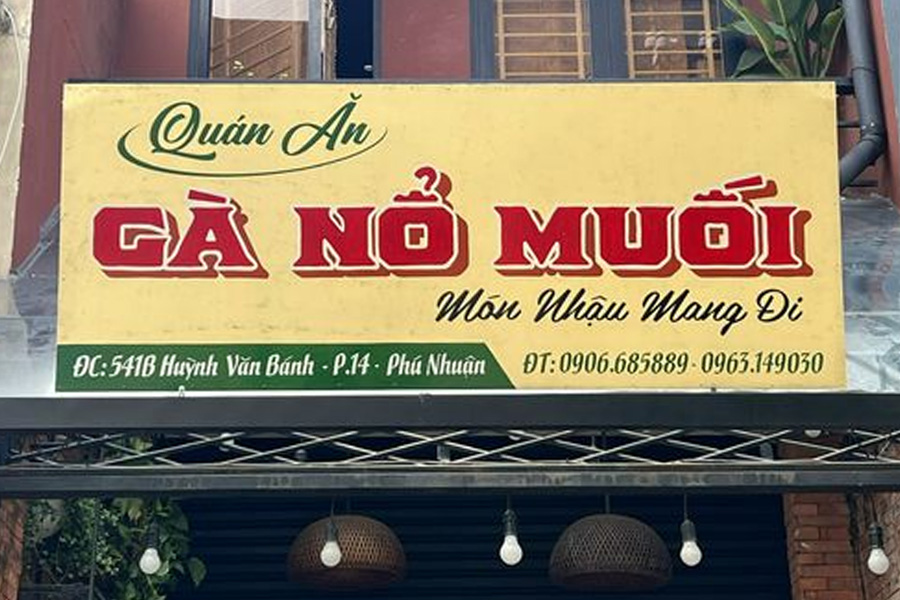
Là một người thiết kế và việt hóa font chữ, mình có một ấn tượng đặc biệt tới các font chữ bảng hiệu xưa của Việt Nam ta trong thời kỳ bao cấp. Thời kỳ này đã để lại dấu ấn rõ rệt trong các bảng hiệu của những cửa hàng tạp hóa, tiệm cắt tóc hay quán cafe…. Font chữ thời bao cấp Việt Nam không chỉ mang đến một nét mộc mạc, giản dị mà còn thể hiện sâu sắc tinh thần dân tộc qua từng đường nét.
Trong thời kỳ bao cấp, nhìn chung thì các bảng hiệu đều được sử dụng những font chữ đơn giản, dễ đọc và chủ yếu được viết thủ công bằng tay. Các font chữ bảng hiệu thời bao cấp treo trên cửa hàng tạp hoá, quán ăn với các chữ cái to thô sơ nhưng cũng chính vì vậy mà đã lột tả lên sự chân thực và gần gũi. Ở thời kỳ này bảng hiệu không mang tính thẩm mỹ cầu kỳ, mà thay vào đó, chúng phản ánh đúng sự khó khăn, mộc mạc của xã hội thời bấy giờ.
Các font chữ bảng hiệu Việt Nam thời bao cấp thể hiện vô cùng rõ nét văn hóa của Việt Nam ở giai đoạn này. Hầu như những tiệm tạp hóa, cửa hàng tóc, quán ăn đều sử dụng những kiểu chữ viết tay đơn giản, không có nhiều chi tiết trang trí phức tạp. Nhờ những nét giản dị qua từng font chữ mà đã trở lên độc đá cho bảng hiệu thời kỳ này, nó cũng là nguồn cảm hứng vô cùng lớn cho các nhà thiết kế ngày nay.
Ngày nay, nhiều quán cà phê muốn tái hiện lại không gian hoài cổ đã chọn sử dụng font chữ bảng hiệu thời bao cấp khá chân thật. Các quán cà phê này muốn tạo nên một không gian gần gũi, nên đã sử dụng các bảng hiệu mang phong cách viết tay thô sơ. Đối với các nhà thiết kế, việc lựa chọn font chữ bảng hiệu sẽ giúp khách hàng cảm thấy kết nối được với quá khứ, mang tới không gian yên bình và gợi nhớ về thời kỳ bao cấp tại Việt Nam.
Tiệm tạp hóa thời bao cấp là một hình ảnh không thể phai mờ của nhiều người Việt Nam. Bảng hiệu của các tiệm tạp hóa thường được vẽ thủ công bằng tay với những đường nét lớn, rõ ràng. Không có sự phức tạp, không hoa mỹ, chính những điểm này mà đã tạo nên sự thu hút của những font chữ này. Khi mình việt hóa lại các font chữ bảng hiệu tiệm tạp quá, mình luôn cố gắng phải giữ lại cái “hồn” của thời kỳ bao cấp.
Đây là một bộ font mà tác giả tốn khá nhiều công sức, thời gian nghiên cứu để có thể hoàn thành. Nó rất đặc biệt so với các bộ font trên thị trường. Để hoàn thiện bộ font bắt buộc tác giả phải nghiên cứu, tìm hiểu các sách báo, dữ liệu hình ảnh từ xa xưa… và lựa chọn ra các font chữ có đường nét giống với những font được viết tay từ bảng hiệu của những năm trước. Khâu khó nhất có lẽ là tác giả phải thiết kế các dấu sao cho phù hợp với từng font và bắt buộc phải có những đường nét thể hiện nên sự mộc mạc, xưa cũ và hoài cổ qua thời gian trên từng font. Bộ font đầy đủ về các kiểu chữ từ in đậm, in nghiêng cho đến viết tay. Bộ font chữ mang những đặc điểm rất riêng, các font thể hiện được các yếu tố về lịch sử, thời gian với những đường nét giản dị, mộc mạc và xưa cũ.
Kết hợp các font chữ bảng hiệu xưa thời bao cấp với phong cách hiện đại trong các ấn phẩm là một thử thách không hề đơn giản. Chúng ta phải giữ được sự giản dị của font chữ bảng hiệu cũ, những vẫn phải kết hợp được các yếu tố mang tính hiện đại từ cách phối màu hay hình ảnh minh họa. Từ đó ta có thể thiết kế ra những ấn phẩm vừa mang dấu ấn văn hóa, vừa có tính hiện đại. Cách kết hợp này cũng được các quán cà phê, quán ăn áp dụng khá nhiều để làm mới không gian quán.
Trong thời kỳ bao cấp thì màu sắc còn khá hạn chế. Những màu như nâu, vàng, xanh đậm thường thấy trên các font chữ bảng hiệu truyền thống. Để ứng dụng được một cách hiệu quả nhất thì mình thường kết hợp những font chữ này với các tông màu xưa cũ để giữ lại nét chân thực, đồng thời giúp bảng hiệu trở nên nổi bật hơn trong các thiết kế hiện đại.
Sử dụng font chữ bảng hiệu xưa thời bao cấp không chỉ mang tới một cảm giác hoài cổ mà còn giúp chúng ta gợi nhớ về những ký ức xưa cũ. Những cửa hàng với các bảng hiệu được thiết kế theo phong cách thời bao cấp sẽ đưa khách hàng trở về những giai đoạn đặc biệt trong lịch sử. Điều này góp phần tạo nên sự gắn kết và cảm xúc, giúp thương hiệu của bạn nổi bật trong lòng khách hàng.
Font chữ bảng hiệu thời bao cấp không chỉ là một phần của lịch sử, văn hóa, mà còn tạo nên những nét đặc biệt trong thiết kế hiện đại ngày nay. Bằng cách kết hợp nét hoài cổ và sự sáng tạo, các nhà thiết kế có thể tạo ra các bảng hiệu độc đáo mang đậm nét đặc trưng của dân tộc. Đặc biệt là các thương hiệu muốn xây dựng hình ảnh truyền thống mang phong cách hoài cổ.
Font chữ bảng hiệu xưa thời bao cấp là một nét đặc trưng của sự mộc mạc và giản dị, các font gợi nên sự chân thực trong cuộc sống của người Việt Nam trong một thời kỳ lịch sử vô cùng đặc biệt. Việc sử dụng những font chữ này không chỉ giúp giữ lại giá trị văn hóa mà còn là cách để tạo nên các ấn phẩm thiết kế vô cùng độc đáo. Nếu bạn đang tìm kiếm một phong cách hoài cổ cho thương hiệu hay không gian cửa hàng của mình, thì font chữ bảng hiệu thời bao cấp chắc chắn là phù hợp với các dự án của bạn.